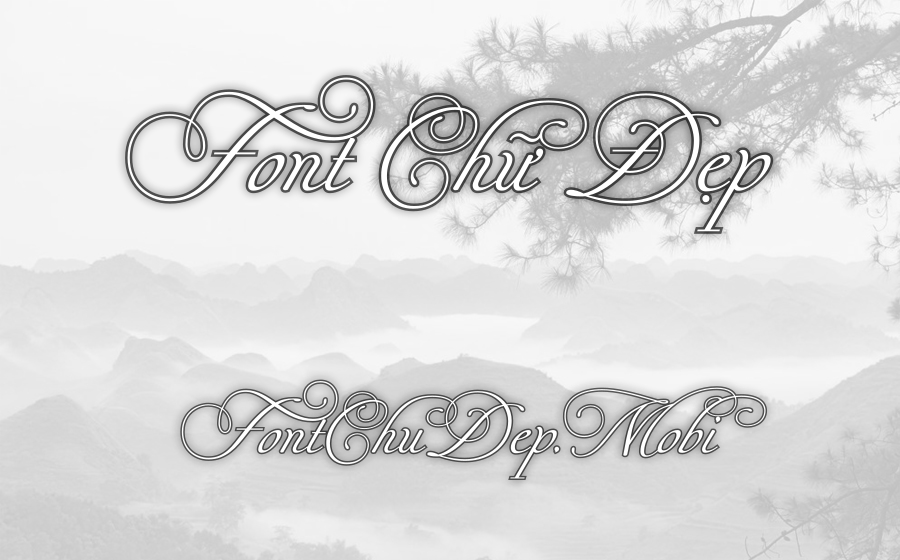
Font UVF Waza Lt Pro Việt Hóa
UVF Waza LT Pro
Khi lần đầu tiên tôi bắt gặp và trải nghiệm Waza LT Pro, tôi không thể không cảm thấy một sự vượt trội mang tính nghệ thuật lẫn sự tinh tế vượt thời gian. Được thiết kế tinh xảo bởi Franciszek Otto và phát hành bởi Linotype GmbH, Waza LT Pro là một phông chữ serif thanh lịch, với nguồn cảm hứng đặc biệt từ tác phẩm khắc của Wilhelm Hondius năm 1641 trên bệ tượng của Vua Ladislaus IV của Ba Lan, thuộc thời kỳ triều đại Vasa Thụy Điển.
Trong hình thức kỹ thuật số, Waza LT Pro sở hữu những chữ cái được kết nối một cách liền mạch dù có rất nhiều chi tiết trang trí phức tạp. Đặc biệt những nét uốn lượn tinh tế ở các chữ cái in hoa làm tôi liên tưởng đến các tác phẩm nghệ thuật cổ điển nhưng vẫn đầy hiện đại, khiến nó trở thành lựa chọn hoàn hảo cho những thiết kế in lớn như chữ cái đầu.
Điều khiến tôi thực sự ấn tượng về Waza LT Pro chính là khả năng thích ứng và tạo sức hút trong các ứng dụng khác nhau. Từ thiết kế thiệp mời sang trọng, logo thương hiệu cao cấp, bìa sách tinh tế đến các ấn phẩm độc quyền đầy cảm xúc, Waza LT Pro không chỉ hoàn thành tốt các nhiệm vụ này mà còn nâng tầm giá trị thẩm mỹ lên một cấp bậc mới.
Hơn thế nữa, trong các sự kiện lớn như lễ hội, lễ cưới hay những buổi giao lưu văn hóa, Waza LT Pro cũng là một điểm nhấn nghệ thuật. Ngành nghề liên quan tới thiết kế đồ họa, nghệ thuật trang trí và xuất bản cũng có thể tận dụng sự sáng tạo không giới hạn mà phông chữ này mang lại. Chính vì những lý do trên, tôi tin rằng bất kỳ nhà thiết kế nào cũng nên thử trải nghiệm Waza LT Pro một lần để cảm nhận hết vẻ đẹp và sức mạnh của nó trong việc truyền tải thông điệp một cách trang nhã và ấn tượng.